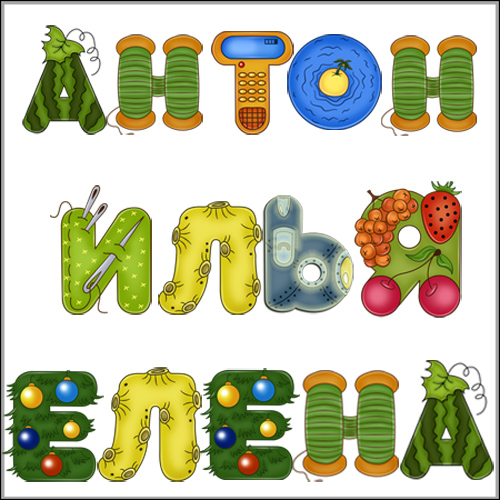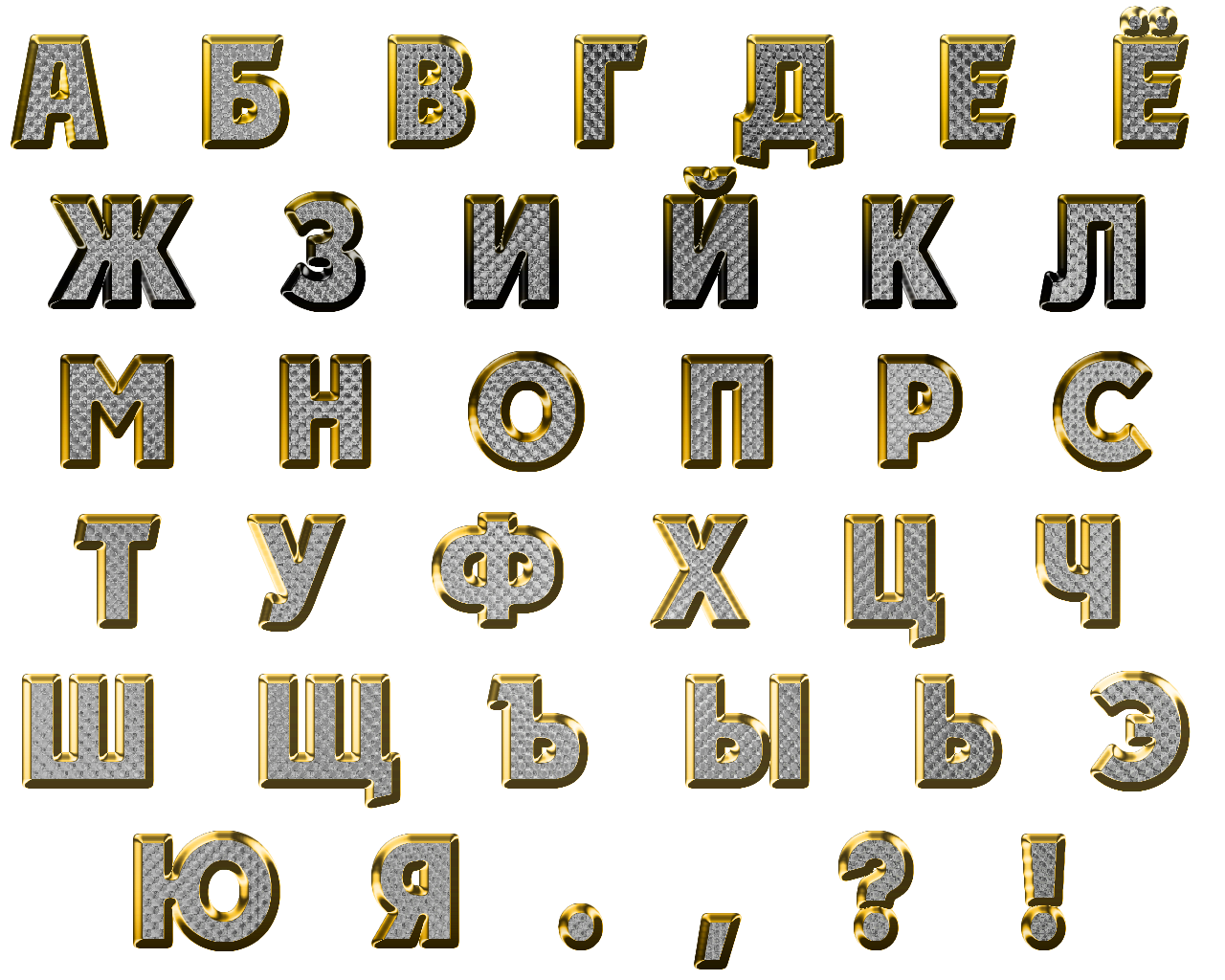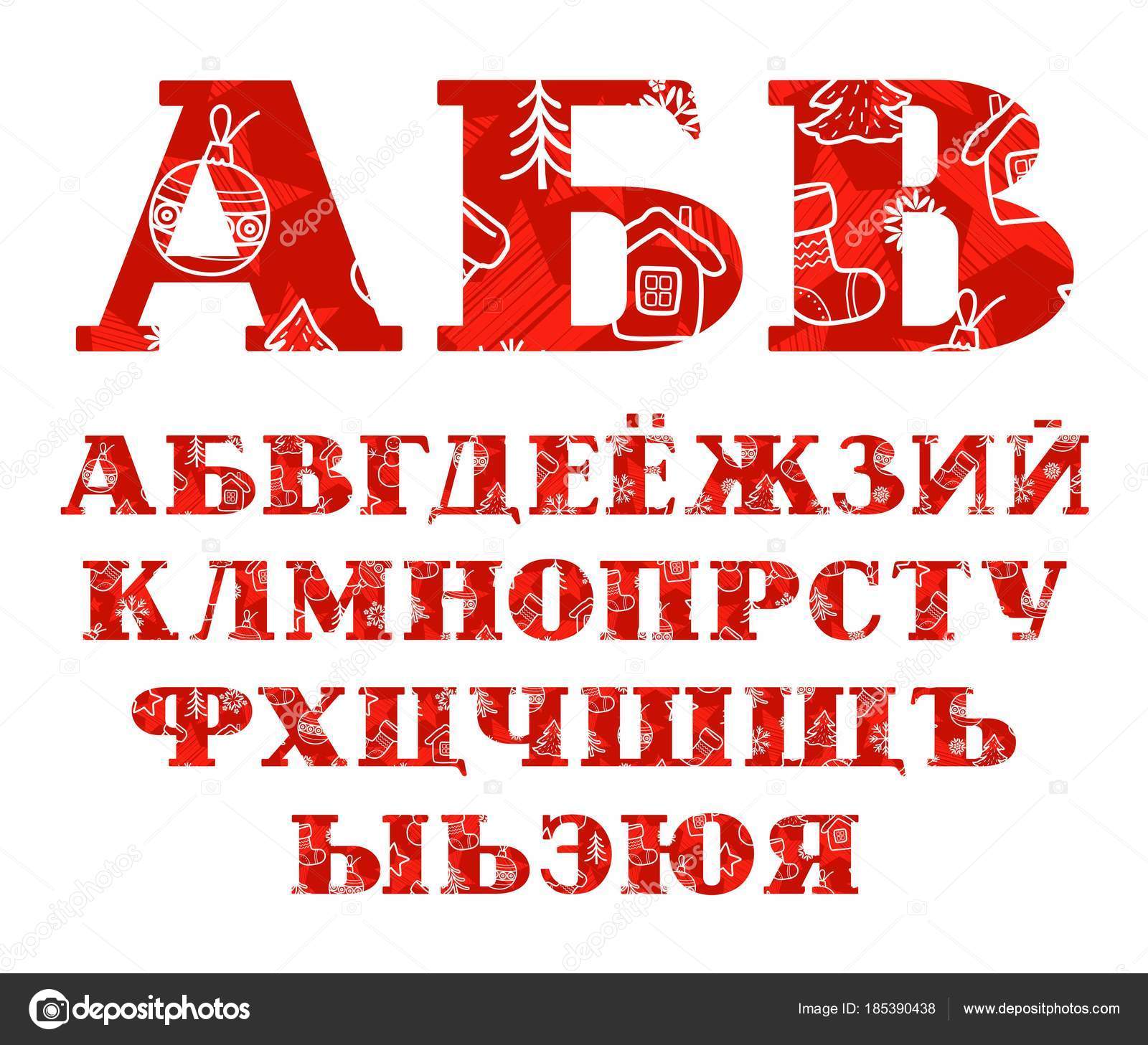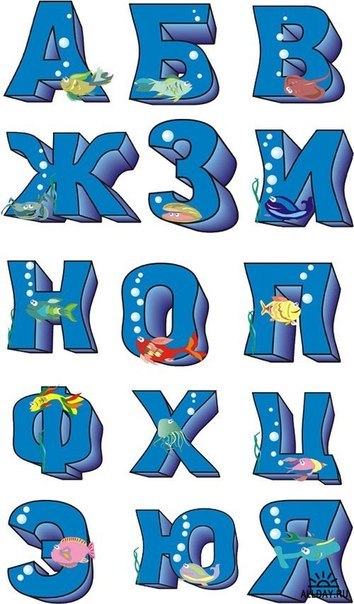
Русский шрифт праздничный: Праздничные шрифты | Шрифты онлайн
60 Русских шрифтов
Свежая подборка великолепных русских шрифтов в количестве 60-и штук. Здесь есть декоративные шрифты, шрифты прописью, классические шрифты, под старину и так далее.
СкачатьLinoscript
СкачатьMajestic
СкачатьMargaritaScript
СкачатьMarkizDeSadScript
СкачатьMenuetScript
СкачатьOlgaCTT
СкачатьOuvertureScript
СкачатьPGIsadoraCyrProRegular
СкачатьPompadur
СкачатьPushkin
СкачатьRomanaScript
СкачатьRomanticaSc
СкачатьRosamundaOne
СкачатьRosamundaTwo
СкачатьRoundScript
СкачатьRurintania
СкачатьSaksonia
СкачатьScriptorama
СкачатьScriptThinPen
СкачатьShellyallegroc
СкачатьStudioScriptCTT
СкачатьVenecia
СкачатьVenskiSadTwo
СкачатьVeraCrouz
СкачатьWolfgangAmadeusMozart
СкачатьZeferinoThree
Надеюсь сборка из этих кириллических русских шрифтов пришлась вам по вкусу и пригодилась в работе.
Также вы можете посмотреть предыдущую мою сборку из русских шрифтов. По просьбам трудящихся сделал архив всех шрифтов в этой статье и теперь вы можете его скачать, нажав на кнопку Скачать внизу статьи. Всего наилучшего! ))
Подборка из 30 бесплатных шрифтов, кириллица
Планируете ли вы изменения в своем веб-сайте, приложении, графическом дизайне? Что ж, тогда последняя коллекция бесплатных шрифтов с поддержкой кириллицы, может помочь вам в этом вопросе. В нашей новой подборке вы сможете скачать 30 качественных шрифтов, которые сделают ваш проект лучше. Выбирай, скачивай и используй в своих дизайн проектах. Также вы может скачать нашу предыдущую подборку со шрифтами которые поддерживают кириллицу.